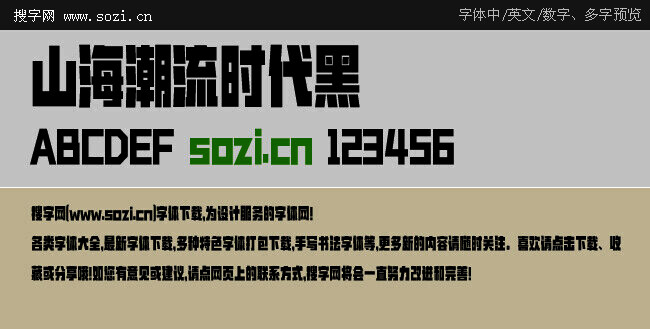
山海潮流時代黑
搜字網(wǎng)提供一款山海潮流時代黑中文藝術(shù)字體下載,山海潮流時代黑是一款綜藝標題黑體字體,包含簡體漢字6763個。該字體是一款具有強勁視覺沖擊力的綜藝風格標題字體。字形瘦高,造型硬朗,全直線的筆畫構(gòu)成棱角分明、堅實有力。適合包裝設(shè)計、海報設(shè)計、廣告設(shè)計等應(yīng)用。